ฟอนต์สวยแต่อ่านยาก = พัง! 3 กฎเหล็กเลือก ‘Font’ บนฉลากสินค้าให้ลูกค้าหยิบ
การออกแบบฉลากสินค้าที่โดดเด่นมักถูกมองว่าเป็นกุญแจสำคัญในการดึงดูดสายตาของผู้บริโภค อย่างไรก็ตาม หลายครั้งที่ความสวยงามกลับมาพร้อมกับปัญหาที่คาดไม่ถึง นั่นคือปัญหา ฟอนต์สวยแต่อ่านยาก = พัง! 3 กฎเหล็กเลือก ‘Font’ บนฉลากสินค้าให้ลูกค้าหยิบ จึงเป็นแนวคิดที่ผู้ประกอบการและนักออกแบบต้องให้ความสำคัญสูงสุด เพราะตัวอักษรที่สื่อสารข้อมูลไม่ชัดเจนอาจหมายถึงการสูญเสียโอกาสในการขายไปอย่างน่าเสียดาย การเลือกใช้ Typography หรือศาสตร์แห่งการออกแบบตัวอักษรที่เหมาะสมจึงไม่ใช่แค่เรื่องของความงาม แต่เป็นองค์ประกอบเชิงกลยุทธ์ที่ส่งผลโดยตรงต่อการตัดสินใจซื้อของผู้บริโภค
ประเด็นสำคัญของการเลือกฟอนต์บนฉลากสินค้า
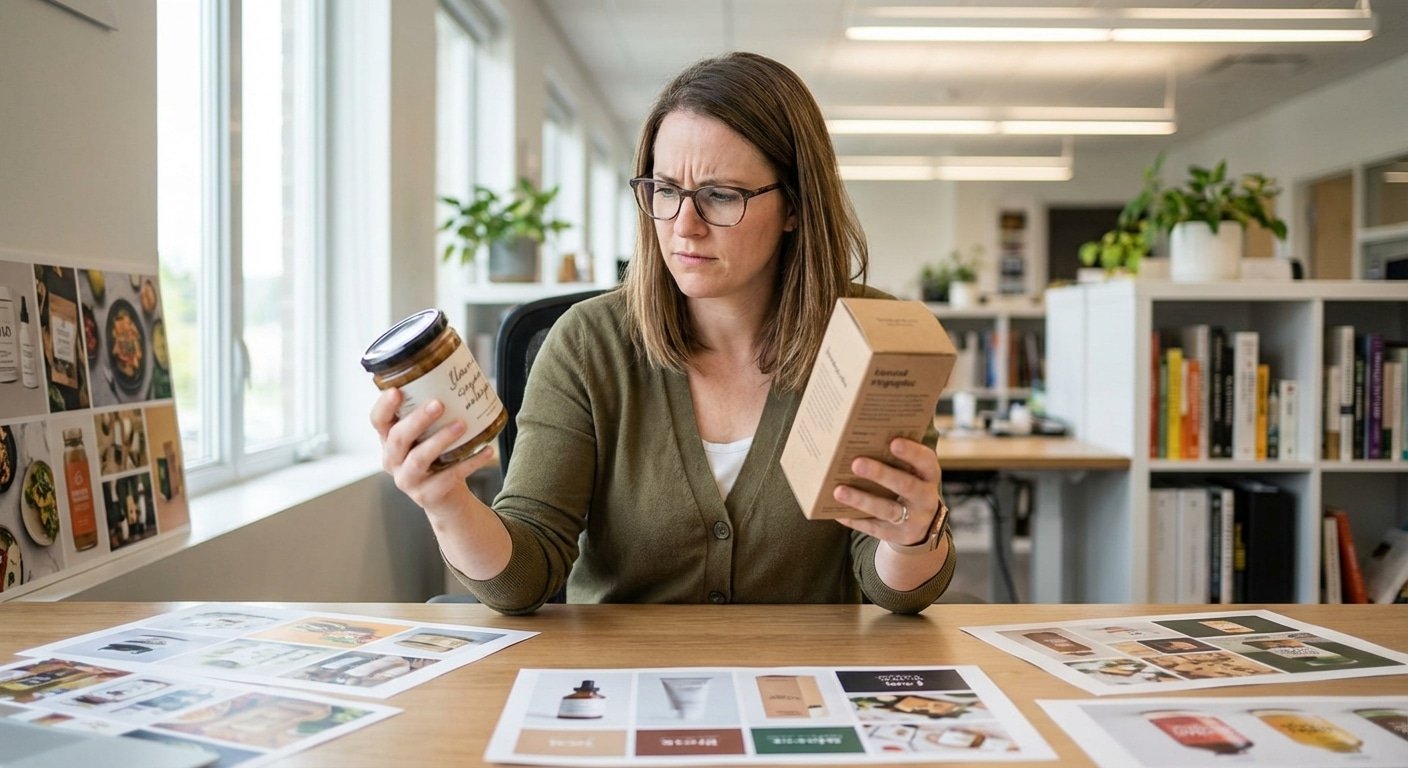
- ความชัดเจนมาก่อนความสวยงาม: ฟอนต์ที่อ่านง่ายคือหัวใจหลักในการสื่อสารข้อมูลสำคัญ เช่น ส่วนประกอบ, วิธีใช้, และวันหมดอายุ ไปยังผู้บริโภคได้อย่างรวดเร็วและถูกต้อง
- Mood & Tone ต้องสอดคล้องกับแบรนด์: รูปแบบของฟอนต์สามารถสะท้อนบุคลิกของแบรนด์ได้ ไม่ว่าจะเป็นความน่าเชื่อถือ, ความทันสมัย, หรือความเป็นธรรมชาติ การเลือกที่ไม่เหมาะสมอาจสร้างความสับสนให้แก่ลูกค้าได้
- ขนาดและความหนาที่เหมาะสมกับการพิมพ์: ฟอนต์ที่ดูดีบนหน้าจอคอมพิวเตอร์อาจไม่ชัดเจนเมื่อถูกพิมพ์ลงบนวัสดุจริง การเลือกฟอนต์ที่มีความหนาและเส้นสายคมชัดจึงเป็นสิ่งสำคัญ
ทำไมฟอนต์สวยแต่อ่านยากจึงเป็นหายนะสำหรับยอดขาย
ในสมรภูมิการแข่งขันบนชั้นวางสินค้า ทุกวินาทีมีค่าต่อการตัดสินใจของผู้บริโภค การออกแบบฉลากสินค้าจึงเปรียบเสมือนพนักงานขายที่ต้องสื่อสารกับลูกค้าอย่างมีประสิทธิภาพภายในเวลาอันสั้น แต่บ่อยครั้งที่ความตั้งใจในการสร้างสรรค์งานออกแบบที่สวยงามกลับกลายเป็นดาบสองคม โดยเฉพาะเมื่อนักออกแบบเลือกใช้ฟอนต์ที่มีความวิจิตรบรรจงแต่ขาดคุณสมบัติด้านการอ่านง่าย (Readability) ปรากฏการณ์ ฟอนต์สวยแต่อ่านยาก = พัง! 3 กฎเหล็กเลือก ‘Font’ บนฉลากสินค้าให้ลูกค้าหยิบ จึงไม่ใช่คำกล่าวที่เกินจริง แต่เป็นบทเรียนที่หลายแบรนด์เคยประสบมาแล้ว
ฟอนต์ที่อ่านยากสร้างภาระทางความคิด (Cognitive Load) ให้กับผู้บริโภค ทำให้สมองต้องใช้พลังงานมากขึ้นในการประมวลผลและถอดรหัสตัวอักษรแต่ละตัว แทนที่จะรับข้อมูลได้อย่างราบรื่น ซึ่งนำไปสู่ความรู้สึกหงุดหงิดและทัศนคติเชิงลบต่อผลิตภัณฑ์นั้นๆ โดยไม่รู้ตัว
ผลกระทบต่อการรับรู้ของผู้บริโภค
ฟอนต์ที่มีลวดลายซับซ้อน, ตัวเขียนที่หวัดเกินไป, หรือมีเส้นสายที่บางเฉียบ อาจรบกวนกระบวนการจดจำรูปทรงของตัวอักษรที่สมองคุ้นเคย ทำให้การอ่านช้าลงและต้องใช้ความพยายามมากขึ้น เมื่อผู้บริโภคต้องเผชิญกับข้อมูลสำคัญอย่างส่วนประกอบ, คำแนะนำการใช้, หรือคำเตือน ที่ถูกนำเสนอผ่านฟอนต์ลักษณะนี้ พวกเขาอาจเลือกที่จะมองข้ามข้อมูลเหล่านั้นไปโดยสิ้นเชิง ผลลัพธ์ที่ตามมาคือความไม่มั่นใจในผลิตภัณฑ์ และท้ายที่สุดคือการเลือกหยิบสินค้าของคู่แข่งที่สื่อสารได้ชัดเจนกว่า
การสูญเสียโอกาสทางการขาย ณ จุดตัดสินใจ
ชั้นวางสินค้าคือพื้นที่ที่การตัดสินใจซื้อเกิดขึ้นอย่างรวดเร็ว ผู้บริโภคใช้เวลาเพียงไม่กี่วินาทีในการสแกนข้อมูลบนฉลากเพื่อเปรียบเทียบและตัดสินใจ หากฉลากสินค้าของคุณเต็มไปด้วยตัวอักษรที่ต้องเพ่งมองหรือตีความ นั่นหมายถึงคุณกำลังสร้างอุปสรรคในการสื่อสารกับลูกค้าโดยไม่จำเป็น ในสถานการณ์เช่นนี้ แม้ว่าผลิตภัณฑ์ของคุณจะมีคุณภาพดีกว่าหรือมีจุดขายที่น่าสนใจกว่า แต่หากไม่สามารถสื่อสารจุดเด่นเหล่านั้นออกไปได้อย่างชัดเจนและทันท่วงที โอกาสในการขายนั้นก็จะหลุดลอยไปอย่างน่าเสียดาย การเลือกใช้ฟอนต์ที่เหมาะสมจึงไม่ใช่แค่เรื่องของความสวยงาม แต่เป็นปัจจัยสำคัญที่ส่งผลโดยตรงต่อยอดขายและความสำเร็จของแบรนด์
3 กฎเหล็กในการเลือก ‘Font’ บนฉลากสินค้าที่ช่วยกระตุ้นยอดขาย
เพื่อหลีกเลี่ยงข้อผิดพลาดที่อาจส่งผลกระทบต่อยอดขาย การทำความเข้าใจในหลักการพื้นฐานของการเลือกใช้ตัวอักษร หรือ Typography จึงเป็นสิ่งสำคัญสำหรับผู้ประกอบการและนักออกแบบ การปฏิบัติตามกฎเหล็ก 3 ข้อต่อไปนี้จะช่วยให้การออกแบบฉลากสินค้าสามารถสื่อสารกับผู้บริโภคได้อย่างมีประสิทธิภาพและนำไปสู่การตัดสินใจซื้อที่ง่ายขึ้น
กฎข้อที่ 1: ให้ความสำคัญกับความชัดเจนและการอ่านง่าย (Readability First)
กฎข้อแรกและสำคัญที่สุดคือ “ความอ่านง่ายต้องมาก่อนเสมอ” แม้ว่าฟอนต์ที่มีเอกลักษณ์จะช่วยสร้างความโดดเด่น แต่หากลูกค้าไม่สามารถอ่านข้อมูลสำคัญบนฉลากได้ ความสวยงามนั้นก็ไร้ความหมาย ควรหลีกเลี่ยงฟอนต์ที่มีลวดลายมากเกินไป, ฟอนต์ตัวเขียนที่เชื่อมติดกันจนอ่านยาก หรือฟอนต์ที่มีเส้นบางจนเกินไปสำหรับข้อมูลที่เป็นเนื้อหาหลัก เช่น รายละเอียดสินค้า, ส่วนประกอบ, และวิธีใช้งาน
ควรเลือกใช้ฟอนต์ที่มีเส้นหนาพอดี, มีช่องไฟระหว่างตัวอักษร (Kerning) และระหว่างคำ (Tracking) ที่เหมาะสม ไม่ชิดหรือห่างกันจนเกินไป ฟอนต์ในกลุ่ม Sans-serif (ไม่มีหัว) หรือ Serif (มีหัว) ที่มีดีไซน์เรียบง่ายมักจะเป็นตัวเลือกที่ปลอดภัยและมีประสิทธิภาพ ตัวอย่างเช่น ฟอนต์ TH SarabunNew ซึ่งเป็นที่นิยมในงานพิมพ์ของไทย ด้วยลักษณะที่อ่านง่าย สบายตา และเป็นที่คุ้นเคย ทำให้ผู้บริโภคสามารถรับข้อมูลได้อย่างรวดเร็ว
กฎข้อที่ 2: สื่อสาร Mood & Tone ให้ตรงกับแบรนด์ (Matching Mood & Tone)
ฟอนต์แต่ละรูปแบบมีความสามารถในการสื่อสารอารมณ์และความรู้สึกที่แตกต่างกัน การเลือกฟอนต์ให้สอดคล้องกับบุคลิกของแบรนด์ (Brand Personality) และกลุ่มเป้าหมายจึงเป็นสิ่งสำคัญอย่างยิ่ง
- ฟอนต์แบบมีหัว (Serif): มักให้ความรู้สึกที่เป็นทางการ, น่าเชื่อถือ, คลาสสิก และหรูหรา เหมาะสำหรับสินค้าที่ต้องการสร้างภาพลักษณ์ด้านคุณภาพและความเป็นมาที่ยาวนาน เช่น ผลิตภัณฑ์บำรุงผิวระดับพรีเมียม, ไวน์, หรือสินค้าออร์แกนิก
- ฟอนต์แบบไม่มีหัว (Sans-serif): ให้ความรู้สึกที่ทันสมัย, เรียบง่าย, สะอาดตา และเป็นมิตร เหมาะสำหรับสินค้าเทคโนโลยี, ผลิตภัณฑ์สำหรับคนรุ่นใหม่, หรือแบรนด์ที่ต้องการสื่อสารความตรงไปตรงมา
- ฟอนต์ลายมือ (Script/Handwriting): ให้ความรู้สึกที่เป็นกันเอง, อบอุ่น, และมีความเป็นส่วนตัว เหมาะสำหรับสินค้าทำมือ (Handmade), ผลิตภัณฑ์สำหรับเด็ก, หรือแบรนด์ที่ต้องการสร้างความรู้สึกใกล้ชิดกับลูกค้า
การผสมผสานฟอนต์ที่สวยงามสำหรับชื่อแบรนด์หรือหัวข้อหลัก เข้ากับฟอนต์ที่เรียบง่ายและอ่านง่ายสำหรับเนื้อหารายละเอียด เป็นเทคนิคที่ช่วยสร้างสมดุลระหว่างความสวยงามและการใช้งานได้อย่างลงตัว
กฎข้อที่ 3: ตรวจสอบลิขสิทธิ์ฟอนต์ก่อนใช้งานเชิงพาณิชย์ (License Verification)
นี่คือกับดักที่ผู้ประกอบการจำนวนมากมักมองข้าม ฟอนต์จำนวนมากที่สามารถดาวน์โหลดได้ฟรีทางอินเทอร์เน็ตมักจำกัดการใช้งานไว้สำหรับส่วนบุคคล (Personal Use) เท่านั้น การนำฟอนต์เหล่านี้มาใช้บนฉลากสินค้าซึ่งถือเป็นการใช้งานเชิงพาณิชย์ (Commercial Use) โดยไม่ได้รับอนุญาต ถือเป็นการละเมิดลิขสิทธิ์และอาจนำไปสู่การฟ้องร้องเรียกค่าเสียหายที่มีมูลค่าสูงจนอาจทำให้ธุรกิจสั่นคลอนได้
ก่อนตัดสินใจเลือกใช้ฟอนต์ใดๆ ก็ตาม จำเป็นต้องอ่านและทำความเข้าใจเงื่อนไขการอนุญาต (License Agreement) อย่างละเอียดถี่ถ้วนเสมอ หากไม่แน่ใจ ควรเลือกใช้ฟอนต์จากแหล่งที่น่าเชื่อถือซึ่งระบุชัดเจนว่าสามารถใช้งานเชิงพาณิชย์ได้ หรือลงทุนซื้อลิขสิทธิ์ฟอนต์ที่ต้องการเพื่อความสบายใจและหลีกเลี่ยงปัญหาในระยะยาว การลงทุนในเรื่องนี้ถือเป็นการป้องกันความเสี่ยงทางธุรกิจที่คุ้มค่าอย่างยิ่ง
เปรียบเทียบประเภทฟอนต์หลักสำหรับการออกแบบฉลาก
เพื่อให้เห็นภาพชัดเจนยิ่งขึ้น การเปรียบเทียบลักษณะเด่นของฟอนต์แต่ละประเภทจะช่วยให้สามารถตัดสินใจเลือกใช้ฟอนต์ที่เหมาะสมกับผลิตภัณฑ์และแบรนด์ได้ง่ายขึ้น
| ประเภทฟอนต์ | ลักษณะเด่น | Mood & Tone ที่สื่อสาร | เหมาะกับสินค้าประเภท |
|---|---|---|---|
| Serif (มีหัว) | มีขีดเล็กๆ ที่ปลายตัวอักษร ช่วยนำสายตาในการอ่านข้อความยาวๆ | เป็นทางการ, น่าเชื่อถือ, คลาสสิก, หรูหรา, ดั้งเดิม | เครื่องสำอางพรีเมียม, สินค้าเพื่อสุขภาพ, อาหารออร์แกนิก, แบรนด์ที่มีประวัติยาวนาน |
| Sans-serif (ไม่มีหัว) | ตัวอักษรเรียบง่าย ไม่มีขีดที่ปลาย อ่านง่ายในขนาดเล็กและบนหน้าจอ | ทันสมัย, สะอาด, ตรงไปตรงมา, เป็นมิตร, เข้าถึงง่าย | สินค้าเทคโนโลยี, ขนมขบเคี้ยว, เครื่องดื่ม, สินค้าสำหรับคนรุ่นใหม่, ผลิตภัณฑ์มินิมอล |
| Script (ลายมือ) | เลียนแบบลายมือเขียน มีความสวยงามและเป็นเอกลักษณ์สูง | เป็นกันเอง, อ่อนโยน, ประณีต, หัตถกรรม, มีความคิดสร้างสรรค์ | สินค้าทำมือ, การ์ดเชิญ, ผลิตภัณฑ์เบเกอรี่, แบรนด์ที่เน้นความเป็นส่วนตัว |
| Display (ตัวประดิษฐ์) | ออกแบบมาเพื่อใช้เป็นหัวข้อ มีความโดดเด่นและตกแต่งสูง | สนุกสนาน, มีพลัง, เฉพาะทาง, ดึงดูดสายตา | ใช้สำหรับชื่อแบรนด์หรือชื่อสินค้าบนฉลาก (ไม่เหมาะกับเนื้อหารายละเอียด) |
แนะนำฟอนต์ภาษาไทยยอดนิยมสำหรับฉลากสินค้าและบรรจุภัณฑ์
การเลือกใช้ฟอนต์ภาษาไทยที่ได้รับการออกแบบมาอย่างดีจะช่วยยกระดับความเป็นมืออาชีพของฉลากสินค้าได้อย่างมาก ปัจจุบันมีฟอนต์ไทยจำนวนมากที่เปิดให้ใช้งานเชิงพาณิชย์ได้ฟรี ซึ่งเป็นประโยชน์อย่างยิ่งสำหรับผู้ประกอบการ SME ฟอนต์ที่แนะนำต่อไปนี้เป็นเพียงส่วนหนึ่งที่ได้รับความนิยมและมีคุณสมบัติเหมาะสมสำหรับงานพิมพ์บนบรรจุภัณฑ์
| ชื่อฟอนต์ | ลักษณะเด่น | การใช้งานที่แนะนำ |
| TH SarabunNew | มาตรฐาน, อ่านง่าย, สบายตา, เป็นที่คุ้นเคยของคนไทย | เนื้อหารายละเอียด, คำแนะนำ, ส่วนประกอบ (เหมาะกับข้อความจำนวนมาก) |
| Prompt | ทันสมัย, เรียบง่าย, ไม่มีหัว, มีหลายน้ำหนักให้เลือก | ชื่อสินค้า, หัวข้อ, เนื้อหาสั้นๆ ที่ต้องการความโมเดิร์น |
| Maitree | มีหัว, ให้ความรู้สึกมั่นคง น่าเชื่อถือ แต่ยังคงความร่วมสมัย | แบรนด์ที่ต้องการความน่าเชื่อถือ เช่น ผลิตภัณฑ์สมุนไพร, สินค้าสุขภาพ |
| Trirong | ตัวแคบและสูง, ประหยัดพื้นที่ในแนวนอน, เส้นคมชัด | เหมาะสำหรับฉลากที่มีพื้นที่จำกัด แต่ต้องการใส่ข้อมูลจำนวนมาก |
| Chakra Petch | เหลี่ยม, ดูแข็งแรง, ทันสมัย, มีกลิ่นอายเทคโนโลยี | สินค้าเกี่ยวกับแกดเจ็ต, เครื่องมือช่าง, ผลิตภัณฑ์สำหรับผู้ชาย |
| Kodchasan | โค้งมน, ไม่มีหัว, ดูเป็นมิตร, น่ารัก, สบายตา | ผลิตภัณฑ์สำหรับเด็ก, สินค้าออร์แกนิก, แบรนด์ที่เน้นความเป็นธรรมชาติ |
| Super Market | ตัวหนากำลังดี, อ่านง่ายในระยะไกล, เป็นมิตร | ชื่อสินค้าที่ต้องการความโดดเด่น, โปรโมชัน, ราคา |
*หมายเหตุ: แม้ว่าฟอนต์เหล่านี้ส่วนใหญ่จะอนุญาตให้ใช้ในเชิงพาณิชย์ได้ แต่ควรตรวจสอบเงื่อนไขลิขสิทธิ์ล่าสุดจากผู้พัฒนาโดยตรงอีกครั้งก่อนนำไปใช้งานจริงเสมอ*
สรุป: เลือกฟอนต์ให้ฉลาด คือการลงทุนที่คุ้มค่า
ท้ายที่สุดแล้ว การเลือกฟอนต์สำหรับฉลากสินค้าไม่ใช่เพียงการตัดสินใจด้านความสวยงาม แต่เป็นการตัดสินใจเชิงกลยุทธ์ที่ส่งผลกระทบโดยตรงต่อการสื่อสารของแบรนด์, การรับรู้ของผู้บริโภค, และยอดขาย การยึดมั่นในกฎเหล็ก 3 ข้อ คือ ให้ความสำคัญกับการอ่านง่ายเป็นอันดับแรก, เลือกฟอนต์ให้สอดคล้องกับบุคลิกของแบรนด์, และตรวจสอบลิขสิทธิ์อย่างเคร่งครัด จะเป็นแนวทางที่ช่วยให้ผลิตภัณฑ์ของคุณสามารถสื่อสารกับลูกค้าได้อย่างมีประสิทธิภาพบนชั้นวางสินค้า การลงทุนเวลาและทรัพยากรในการเลือก Typography ที่เหมาะสม คือการลงทุนที่สามารถสร้างผลตอบแทนที่คุ้มค่าในระยะยาว ช่วยให้ลูกค้าตัดสินใจหยิบสินค้าของคุณได้อย่างไม่ลังเล